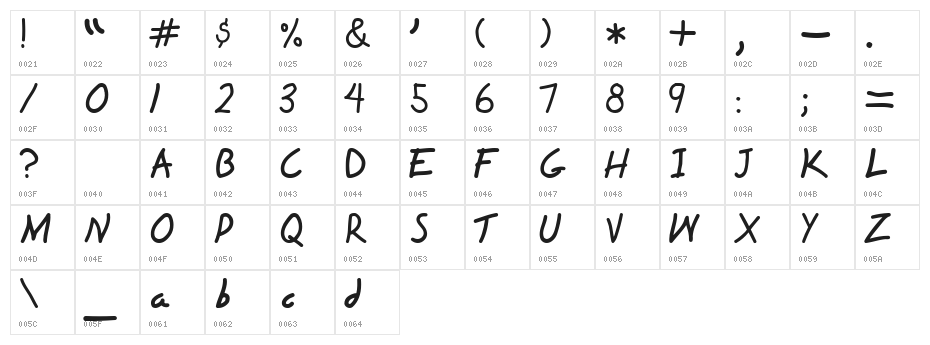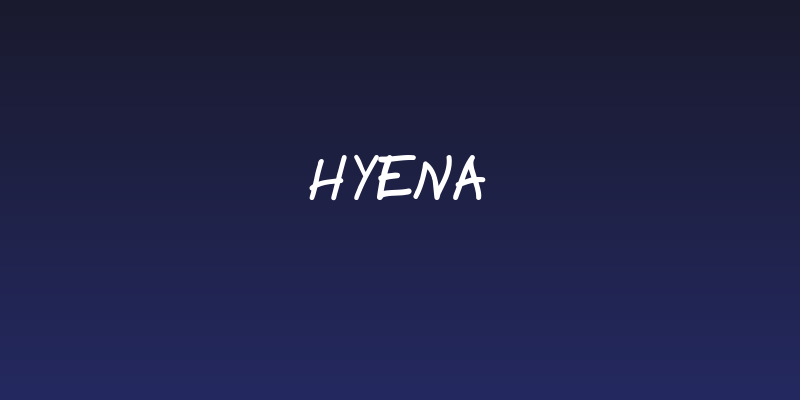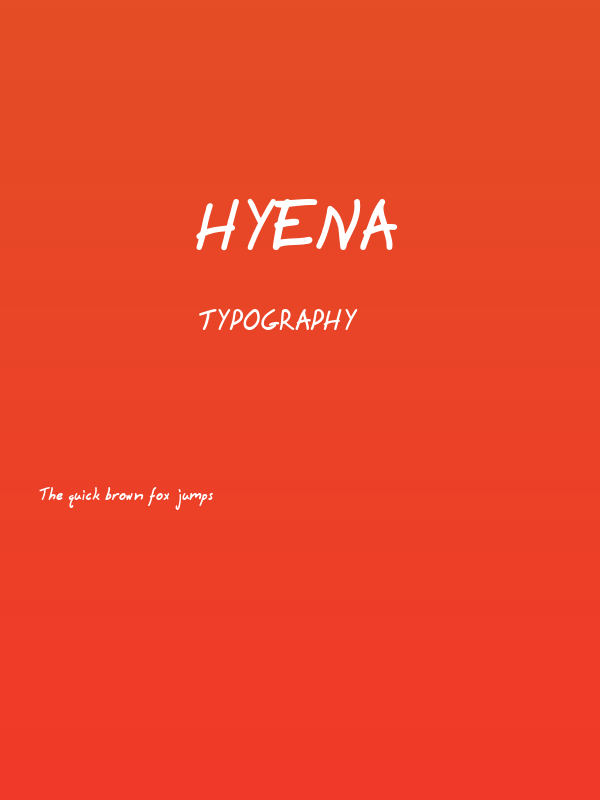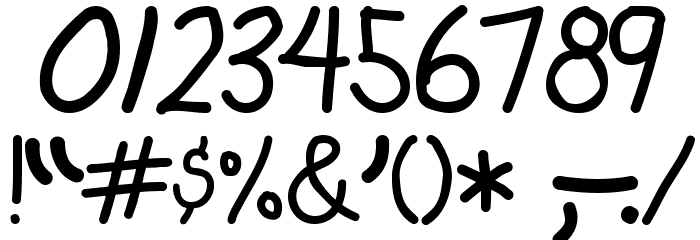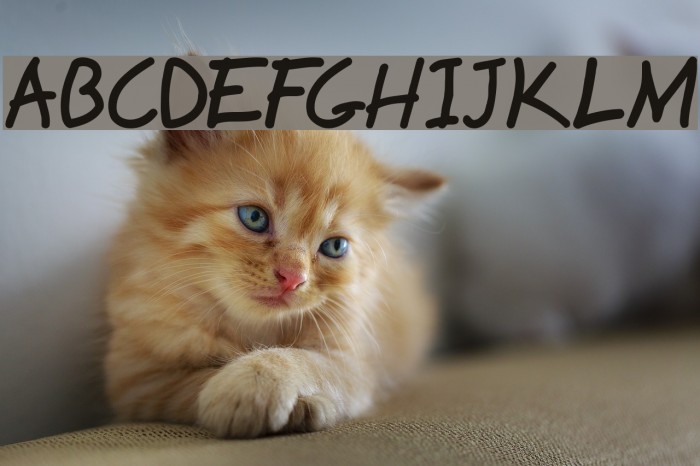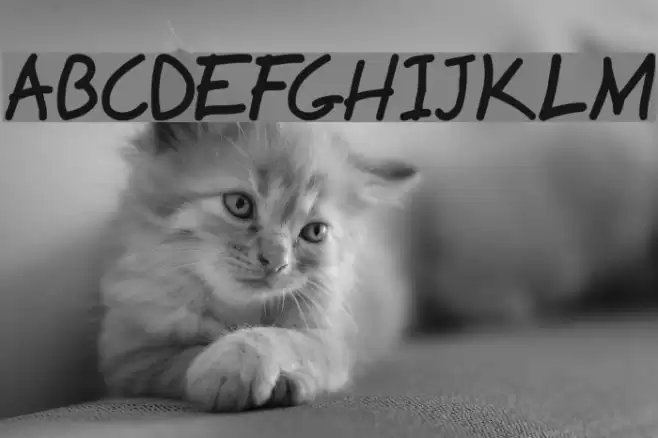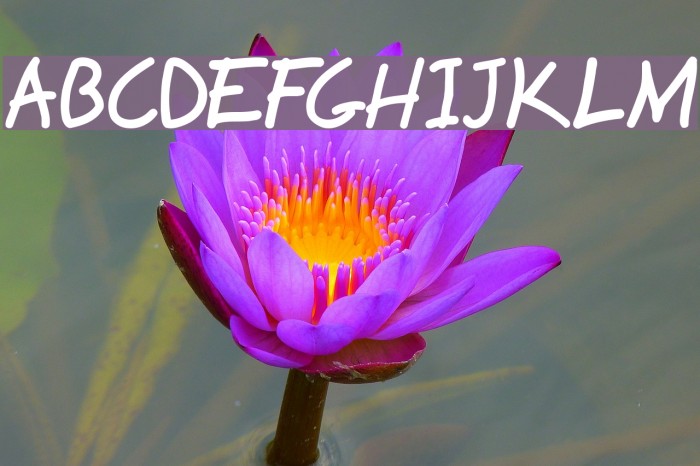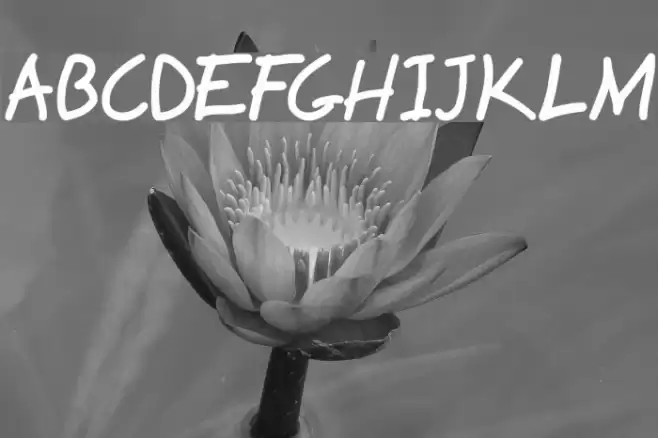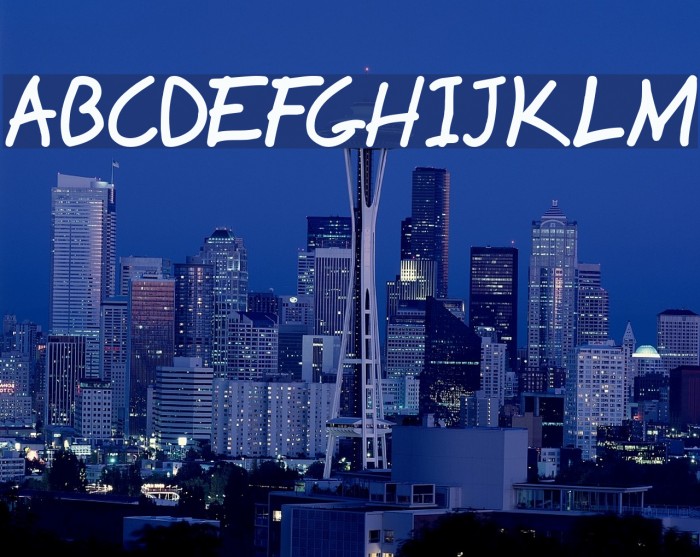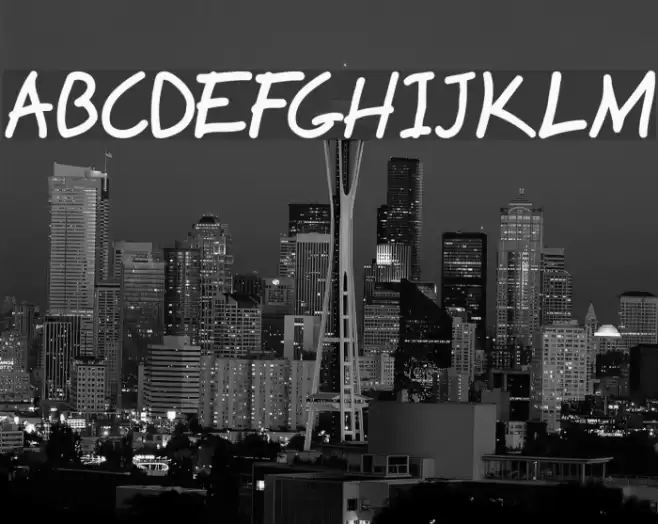
Hyena Font
| النمط العام | Casual, Playful |
| حالة الاستخدام | Headlines, Informal text, Creative projects |
| مشاريع مقترحة | Ideal for greeting cards, invitations, personal blogs, and creative branding projects. |